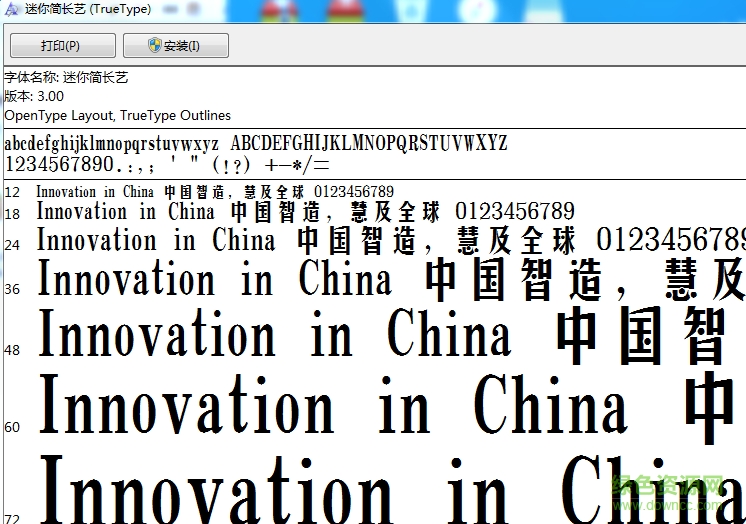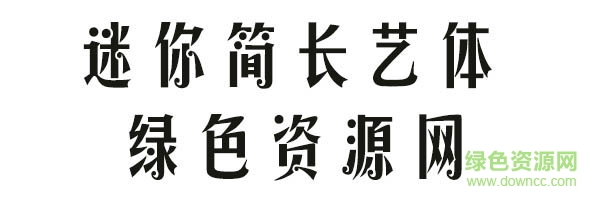
迷你簡(jiǎn)長(zhǎng)藝字體是一款藝術(shù)設(shè)計(jì)用戶必備的迷你字體系列字體,采用傳統(tǒng)中國(guó)簡(jiǎn)體字打造而成,使用范圍廣泛,喜歡就來綠色資源網(wǎng)下載體驗(yàn)唄!
迷你簡(jiǎn)長(zhǎng)藝是一款應(yīng)用于藝術(shù)方面的中文簡(jiǎn)體漢字,字體帶勾,藝術(shù)感十足,適用于藝術(shù)設(shè)計(jì)、廣告設(shè)計(jì)、平面設(shè)計(jì)、包裝印刷等領(lǐng)域,喜歡的朋友快下載收藏吧。